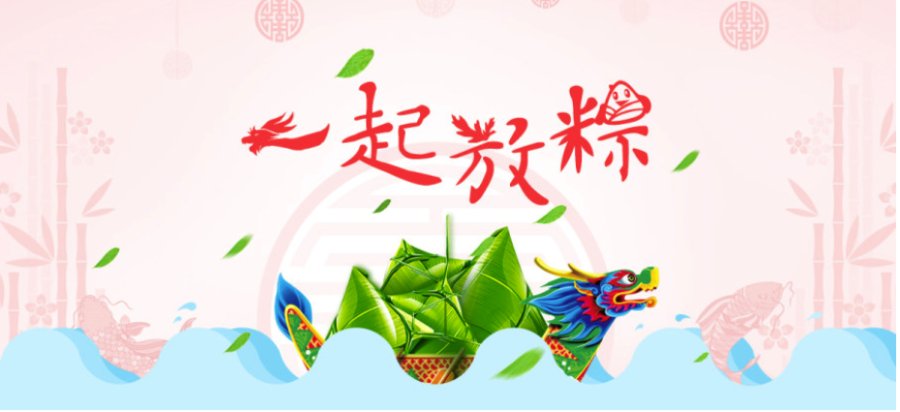
每年的农历五月初五是中国传统节日——端午节,其又称端阳节、龙舟节、重午节、龙节、正阳节、天中节等。那么在端午节到来之际,你是不是还在为端午节文案字体而烦恼呢?别担心,小字特地为大家推荐一款别有新意的端午节活动商用字体,一起来看看吧!
义启端午体是字体视界推出的一款书法字库,该字体针对传统的端午节而开发,字体中融入了粽子、艾草、龙舟等元素,使得这款字体更具端午气息;字形结构上收放有度,气势如虹,章法更是左右衔接,一气呵成。